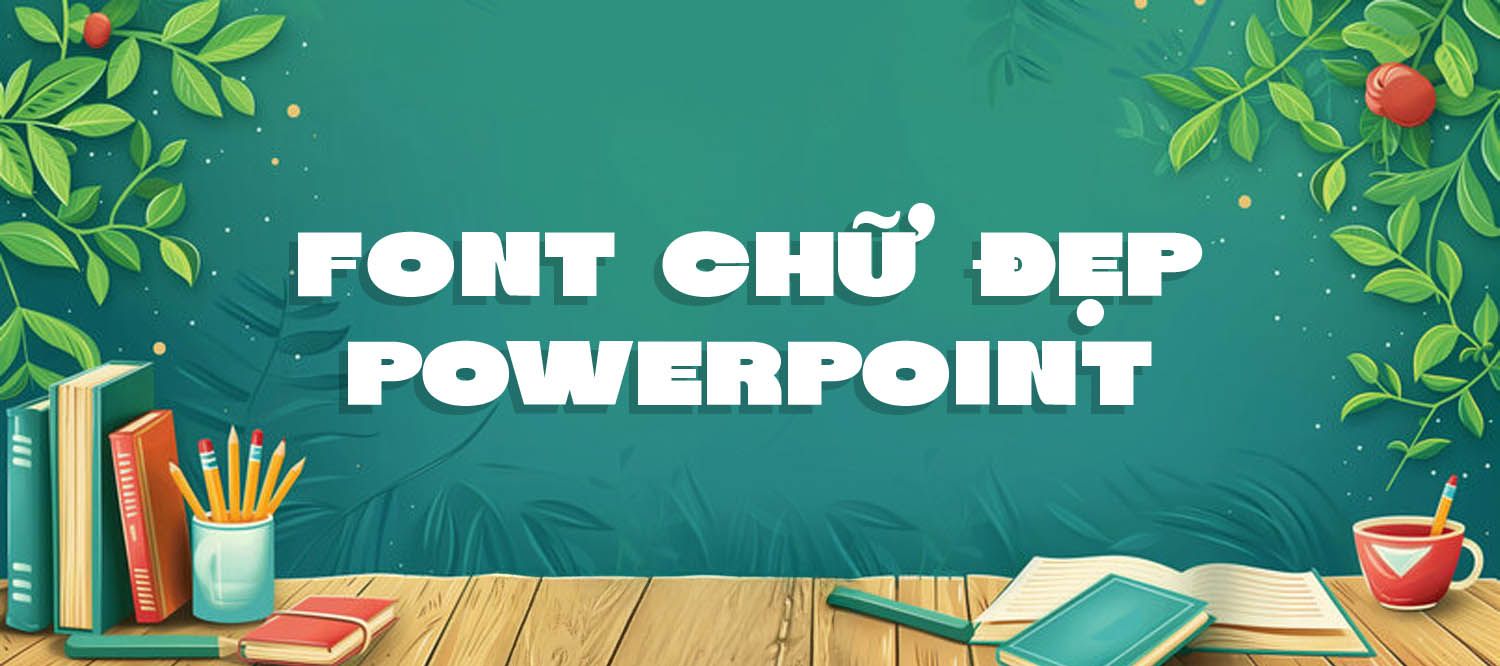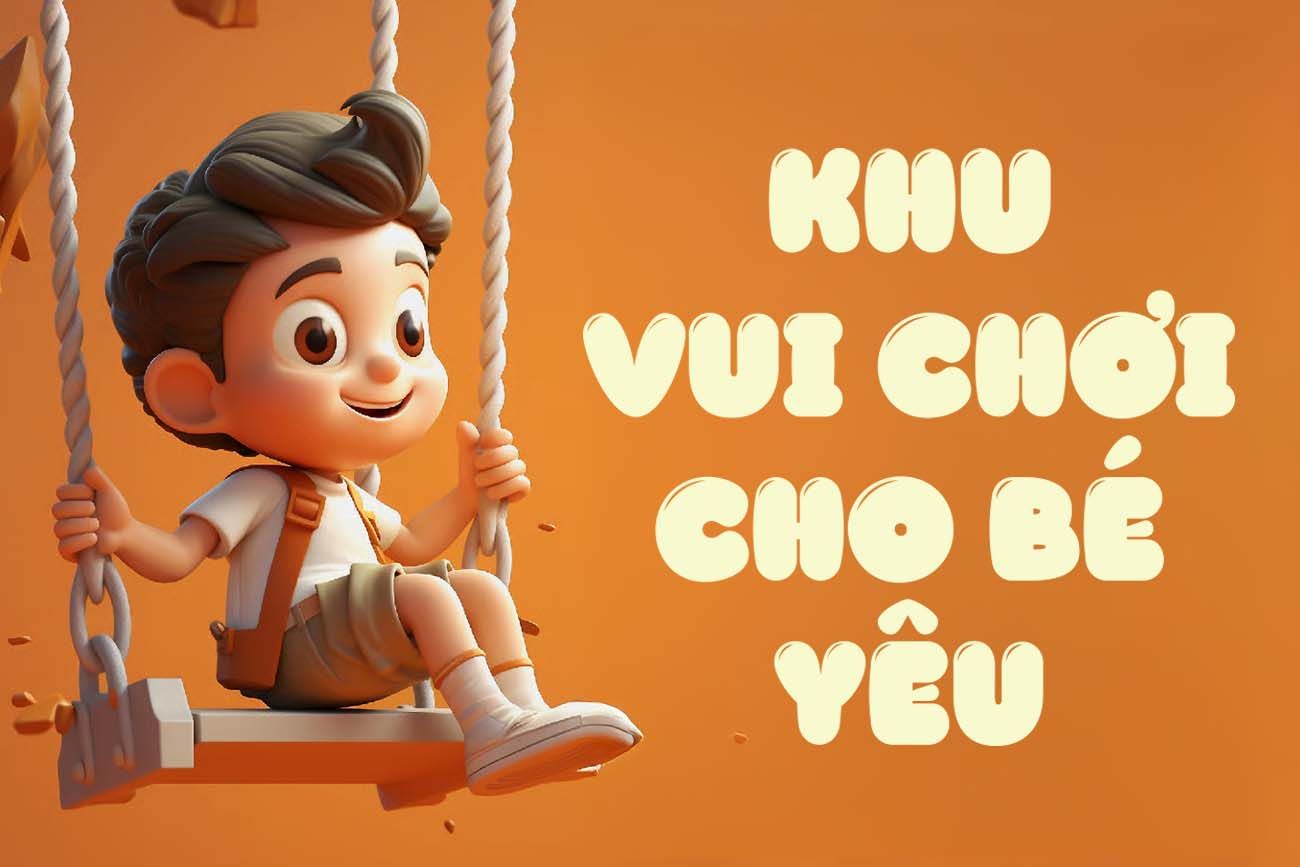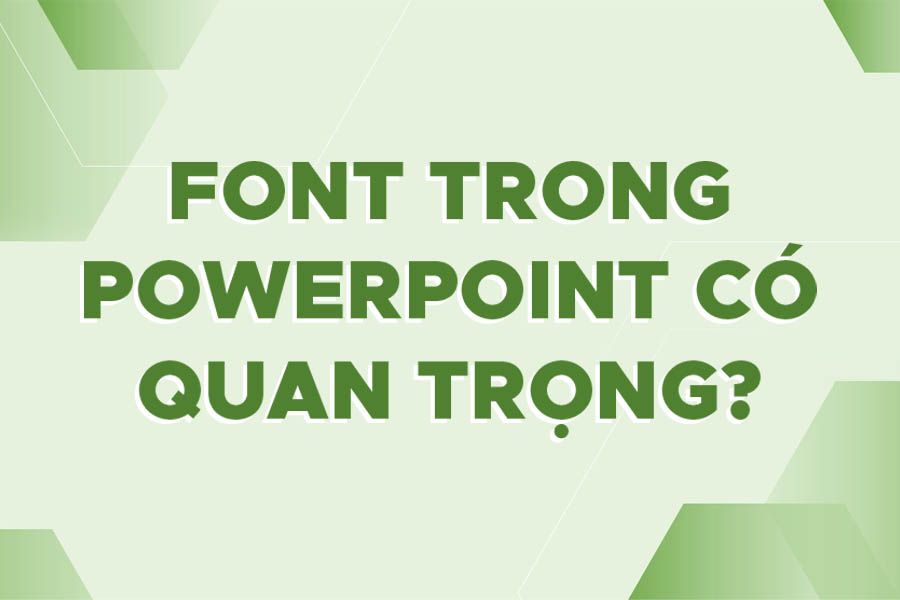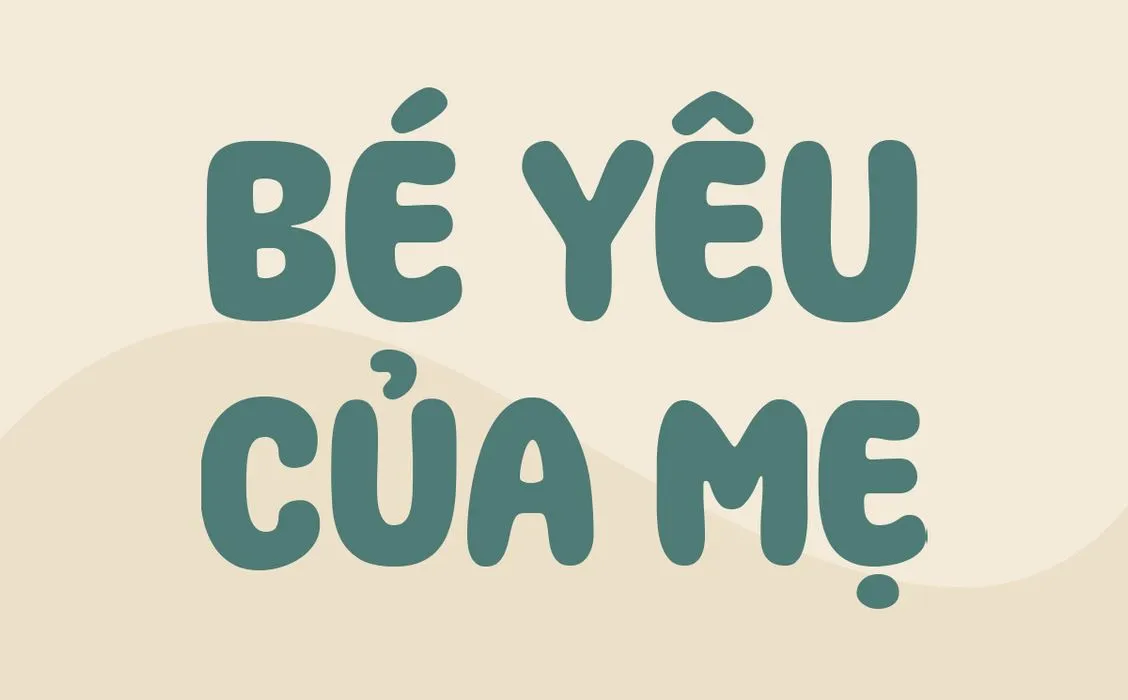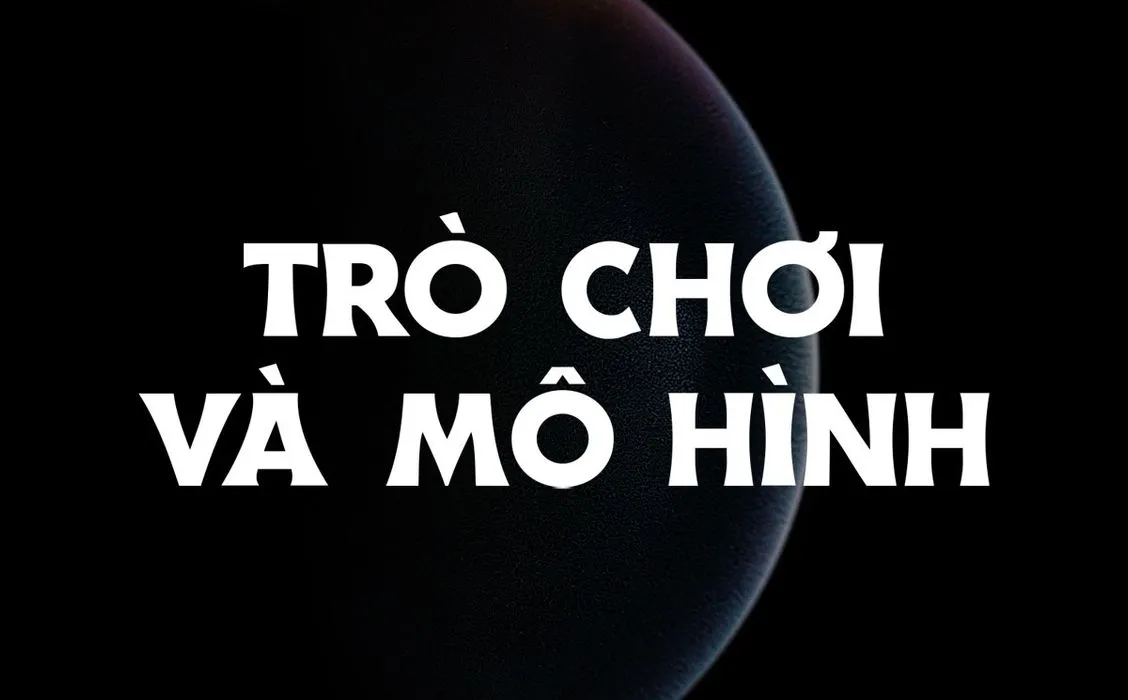
TOP 20 Font Chữ Đẹp PowerPoint Cho Thiết Kế Slide 2025
Trong thời đại số hóa, thuyết trình bằng PowerPoint không chỉ dừng lại ở việc truyền tải thông tin mà còn là nghệ thuật chinh phục người nghe. Ngoài nội dung logic, súc tích thì yếu tố thiết kế trực quan đóng vai trò quan trọng trong việc giữ sự tập trung và tạo cảm hứng cho khán giả. Một trong những chi tiết tưởng chừng nhỏ nhưng lại quyết định rất nhiều đến “bộ mặt” của slide chính là font chữ đẹp PowerPoint
Vì sao font chữ lại quan trọng trong PowerPoint?
Không ít người khi thiết kế slide thường tập trung vào hình ảnh, màu sắc mà bỏ qua yếu tố chữ viết. Thực tế, chữ mới là phần người xem phải “tiêu hóa” nhiều nhất. Một font chữ phù hợp có thể:
Tăng tính thẩm mỹ: Font chữ hài hòa với thiết kế giúp slide trở nên tinh tế và chuyên nghiệp hơn.
Cải thiện khả năng đọc: Những font chữ rõ ràng, gọn gàng giúp khán giả dễ dàng nắm bắt thông tin.
Tạo dấu ấn riêng: Font chữ thể hiện cá tính, phong cách của người thuyết trình và tính chất của nội dung.
Truyền tải đúng thông điệp: Ví dụ, font sans-serif hiện đại phù hợp cho kinh doanh, trong khi font script mềm mại hợp với chủ đề nghệ thuật.
Bộ sưu tập font chữ đẹp PowerPoint theo từng phong cách
Dưới đây là gợi ý bộ sưu tập font chữ đẹp PowerPoint theo từng phong cách để bạn dễ lựa chọn khi thiết kế slide:
Font chữ phong cách hiện đại – tối giản
Trong số những lựa chọn đa dạng, phong cách hiện đại và tối giản luôn được ưa chuộng bởi sự tinh gọn, dễ đọc nhưng vẫn đảm bảo tính chuyên nghiệp.
1. Font chữ bold nét dày hiện đại sang trọng TH Wanderlust
Mô tả: TH Wanderlust là font chữ hiện đại, nét dày, thiết kế bold nổi bật, mang đến cảm giác sang trọng và mạnh mẽ. Phong cách font tinh tế, tối giản nhưng vẫn nổi bật, phù hợp cho tiêu đề, logo hoặc các thiết kế cần sự đẳng cấp, hiện đại và cuốn hút thị giác.
2. Font chữ nét mảnh serif hiện đại TH VADOLA Việt hóa
Mô tả: TH VADOLA là font chữ serif mang phong cách hiện đại, với các đường nét mảnh mai, thanh thoát, tạo cảm giác nhẹ nhàng nhưng vẫn đậm chất sang trọng. Kiểu chữ này lý tưởng để sử dụng cho tiêu đề, nội dung văn bản, thiết kế tạp chí hoặc các ấn phẩm đòi hỏi sự tinh tế và chuyên nghiệp.
3. Font chữ nét mảnh sang trọng TH NewYork Việt hóa
Mô tả: TH NewYork là một serif tinh tế, kết hợp giữa nét cổ điển và hiện đại. Với vẻ sang trọng và chuyên nghiệp, font này thích hợp cho danh thiếp, logo, poster hay các dự án thời trang, làm đẹp, spa.
Tác giả gốc: Artem Nevsky
4. 4 kiểu font chữ serif hiện tại từ TH Red Rose Việt hóa
Mô tả: Tải xuống 4 kiểu font chữ serif hiện đại từ bộ sưu tập TH Red Rose. Các font mang phong cách thanh lịch, dễ đọc, phù hợp cho tiêu đề, văn bản in ấn và các dự án thiết kế sáng tạo, mang lại vẻ tinh tế và hiện đại cho mọi sản phẩm.
Tác giả gốc: Jaikishan Patel
5. Font chữ hiện đại Sans-Serif TH Legacy Sans Việt hóa
Mô tả: TH Legacy Sans là font chữ hiện đại thuộc dòng Sans-Serif, mang thiết kế gọn gàng, tinh tế và dễ đọc. Các chữ cái có đường nét cân đối, tỷ lệ hài hòa, phù hợp với cả tiêu đề lẫn nội dung dài. Phong cách đơn giản nhưng sang trọng, tạo cảm giác hiện đại và chuyên nghiệp, thích hợp sử dụng trong thiết kế đồ họa, thương hiệu và giao diện số.
Tác giả gốc: Ronald Arnholm
Font sáng tạo – Tạo điểm nhấn cho ý tưởng
Nếu bạn muốn bài thuyết trình của mình không chỉ gọn gàng mà còn thật sự ấn tượng, việc lựa chọn font chữ sáng tạo là chìa khóa. Những font này giúp làm nổi bật ý tưởng, tạo điểm nhấn độc đáo và khiến khán giả nhớ đến bạn lâu hơn.
6. Font chữ cho ấn phẩm du lịch Thái Lan TH Phataya Việt hóa
Mô tả: Font chữ TH Phataya mang phong cách vui tươi, mềm mại, thân thiện, phù hợp với chủ đề du lịch. Các nét chữ mượt mà tạo cảm giác thoải mái, gần gũi và dễ đọc. Phong cách này gợi liên tưởng đến những trải nghiệm năng động, đầy màu sắc và văn hóa đặc trưng của Thái Lan, thích hợp cho poster, brochure hoặc các ấn phẩm quảng bá du lịch.
Tác giả gốc: Cadson Demak
7. Font chữ Việt hóa phong cách cổ điển TH Holywest
Mô tả: Font TH Holywest mang phong cách vintage cổ điển, với các đường nét dày, mạnh mẽ và cá tính. Thiết kế pha trộn giữa hoài niệm thế kỷ trước và hiện đại, nổi bật trên mọi nền và dễ thu hút ánh nhìn. TH Holywest lý tưởng cho poster, bìa sách hay các dự án retro, tạo dấu ấn mạnh mẽ và thẩm mỹ tinh tế.